未来感とモダンさを添える “Futura”合成フォントのすすめ 4選
クリーンで幾何学的。だけど、どこか温もりもある。
そんな魅力を持つ欧文フォントFutura(フーツラ)は、和文フォントと組み合わせることで、洗練されたデザインに仕上げられる万能選手です。
この記事では、Futuraを使ったおすすめの合成フォント例をご紹介します。
文字から始まるモダンデザイン、あなたも試してみませんか?
Futuraとは?
Futuraは1927年に登場した、幾何学的なシルエットが特徴のサンセリフ体。
直線と円を基調にしたフォルムは、無駄をそぎ落としたミニマルな美しさを感じさせます。
AppleやVolkswagenなど、世界的ブランドのロゴにも使われてきた定番フォントです。
未来的で理知的な印象を与える一方で、やや丸みを感じるため、冷たくなりすぎず、親しみも残るのが魅力。
この絶妙なバランスが、日本語のフォントとも相性抜群です。
UD新ゴ + Futura
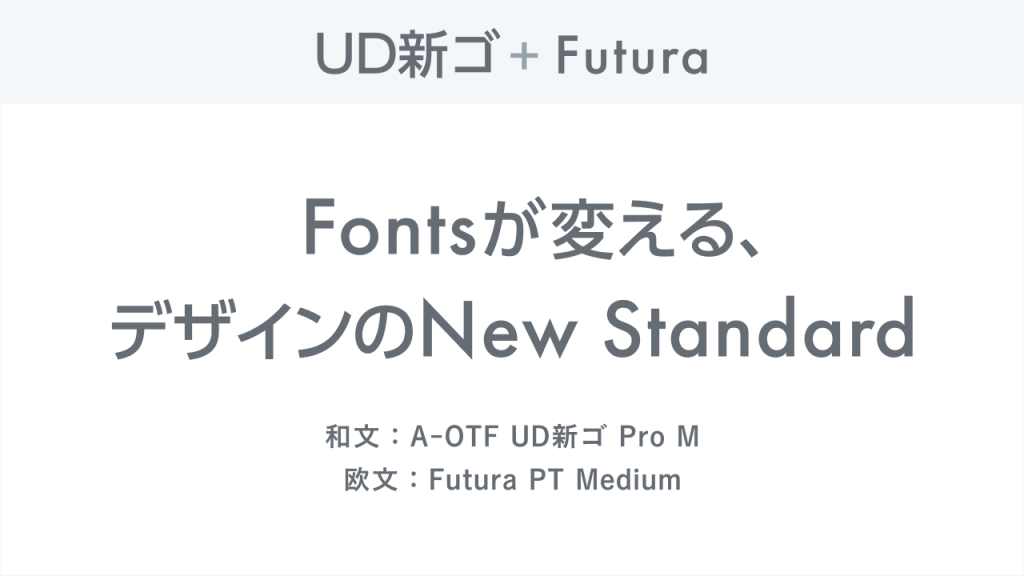
ユニバーサルデザインを意識したUD新ゴの読みやすさに、Futuraの幾何学的でシャープな印象が加わる組み合わせ。
情報性をしっかり伝えながら、洗練されたモダンさも演出できます。
太ゴ + Futura
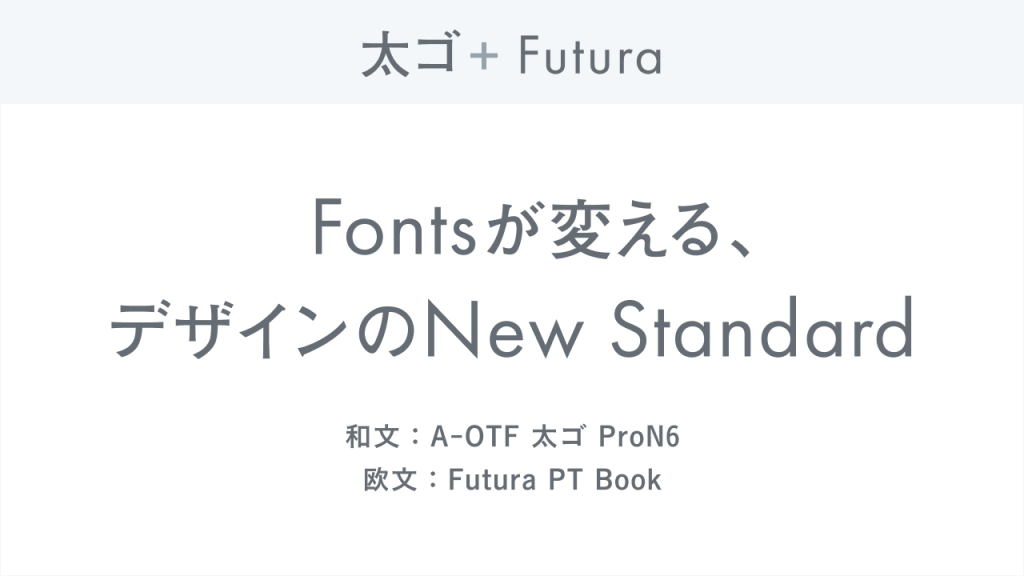
Futuraの硬質で均整の取れた欧文を合わせることで、力強さと洗練が共存するビジュアルに。
こぶりなゴシック + Futura
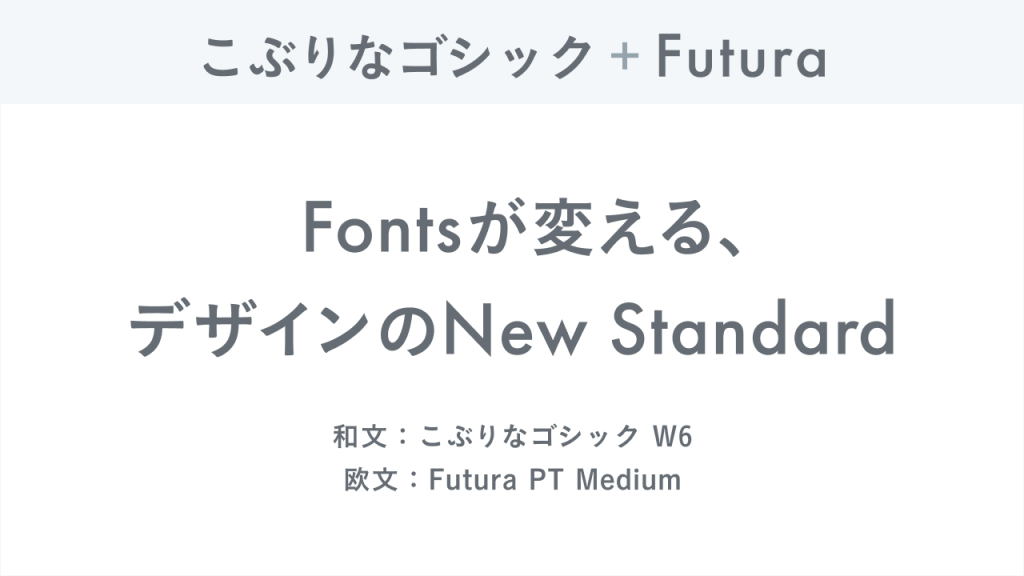
柔らかく小さめなサイズ感のこぶりなゴシックが、Futuraの幾何学的なフォルムと絶妙にマッチ。
やさしい中に洗練された印象があります。
筑紫ゴシック + Futura
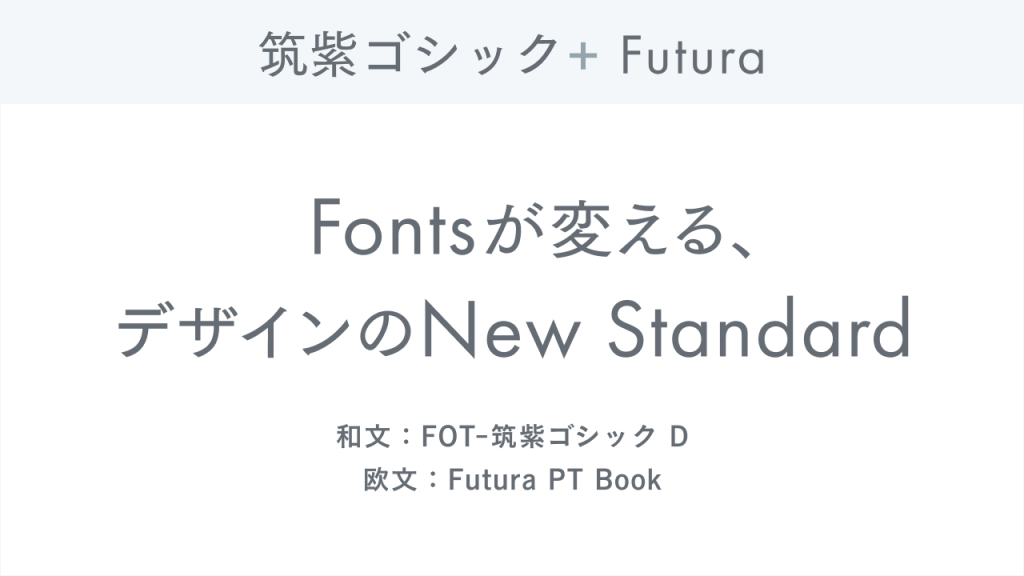
やわらかく人間味のある筑紫ゴシックに、理知的なFuturaを合わせることで、意外性のあるバランスに。
おわりに
Futuraは、“使えばオシャレになる”という感覚で選ばれることも多いフォントですが、
和文との組み合わせによって、その魅力はさらに広がります。
合成フォントをうまく活用すれば、Futuraの美しさを引き立てながら、伝わるデザインに近づけることができます。
ぜひ一度、あなたのデザインにFuturaを取り入れてみてください。
ミニマルだけど印象に残る。そんな新しい世界が待っています。